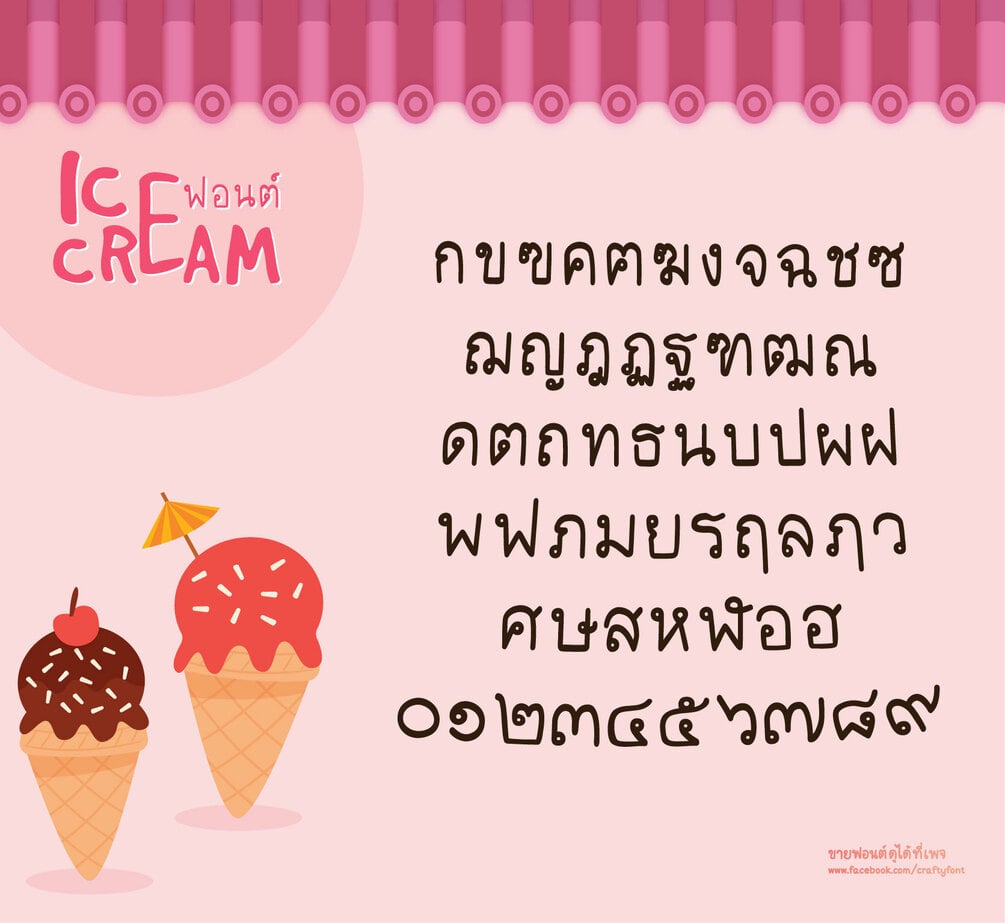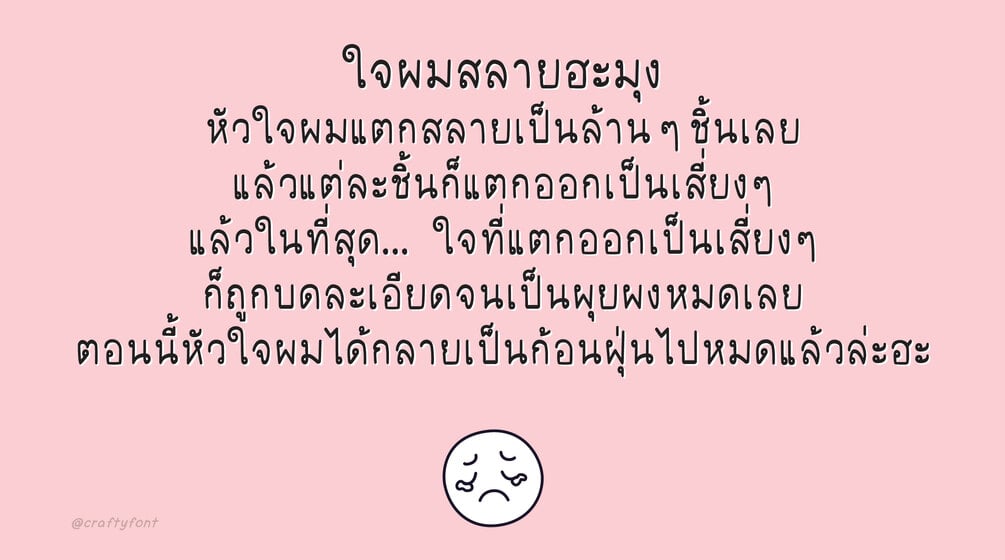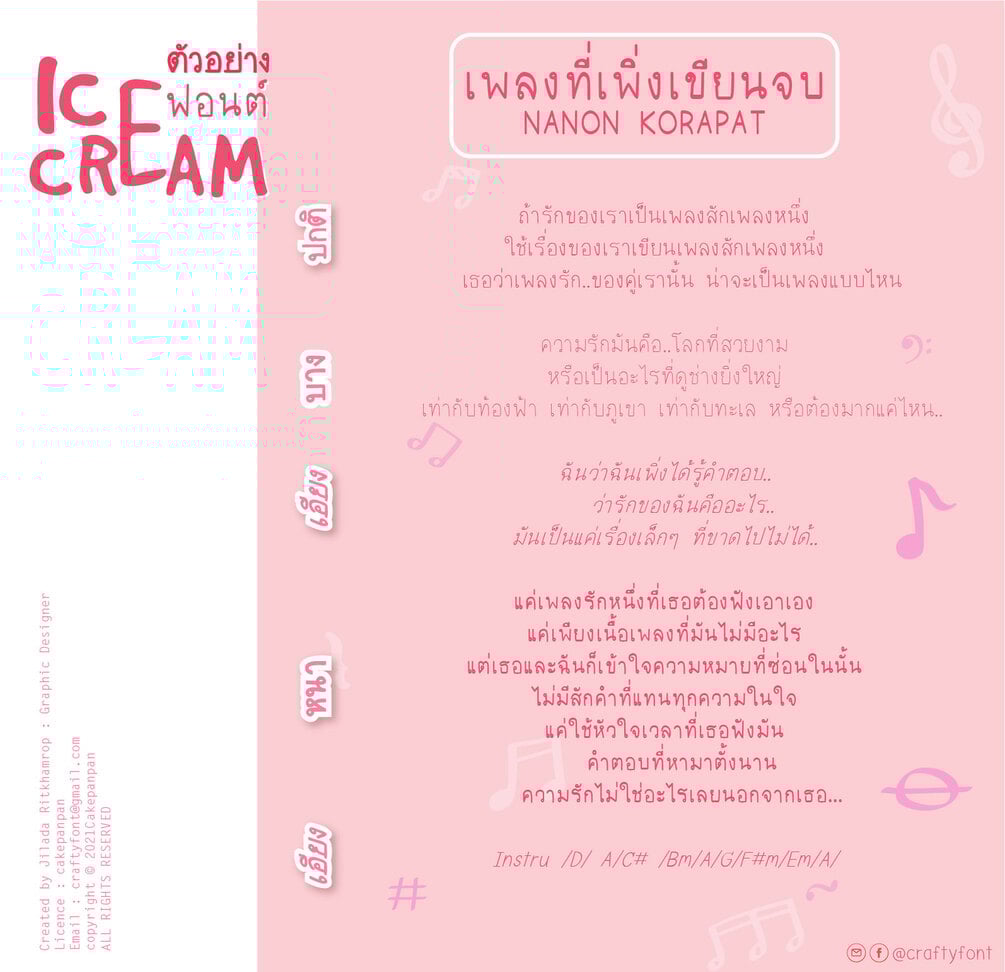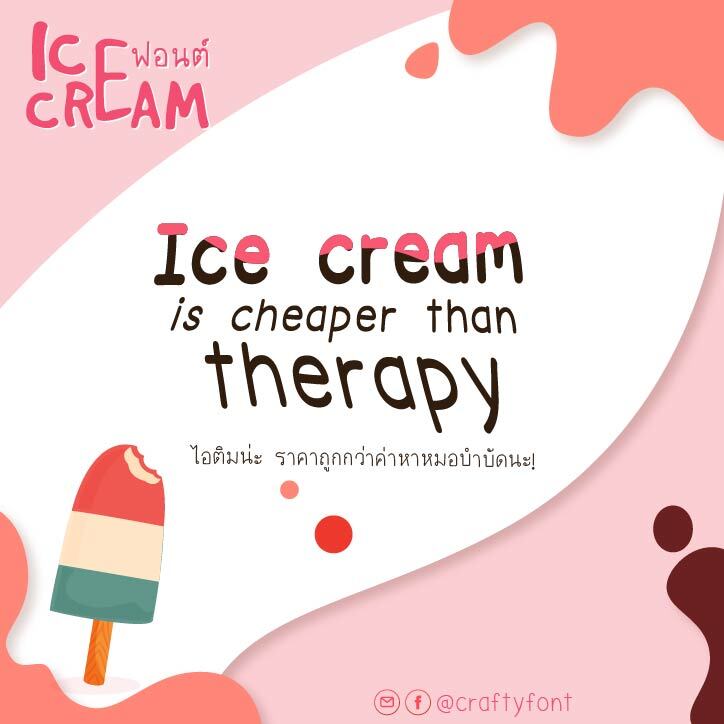
Ice cream Font (ฟอนต์ไอติม)
หน้าร้อนแบบนี้ต้องกินไอติมเย็นๆ ให้ชื่นใจ 🍧🍧
ฟอนต์ไอติมออกแบบมาให้เป็นฟอนต์มีหัว แต่ทำให้หัวเล็ก บีบตัวอักษรให้แคบลง (กว่าที่ Crafty font เคยทำ) ให้ความรู้สึกเป็นมิตรมากขึ้น! 🥰
ฟอนต์น้องไอติมมีทั้งภาษาไทยและภาษาอังกฤษเลยนะคะ แฟมิลี่เซ็ตนี้มี 4 ขนาดด้วยกัน ทั้งตัวหนา ตัวเอียง ตัวบาง และตัวปกติ สัญลักษณ์บวกลบคูณหารมีให้ใช้ครบ ฝากไว้ในอ้อมอกอ้อมใจพี่จ๋าด้วยนะจ๊ะ 🙏🏻🙏🏻